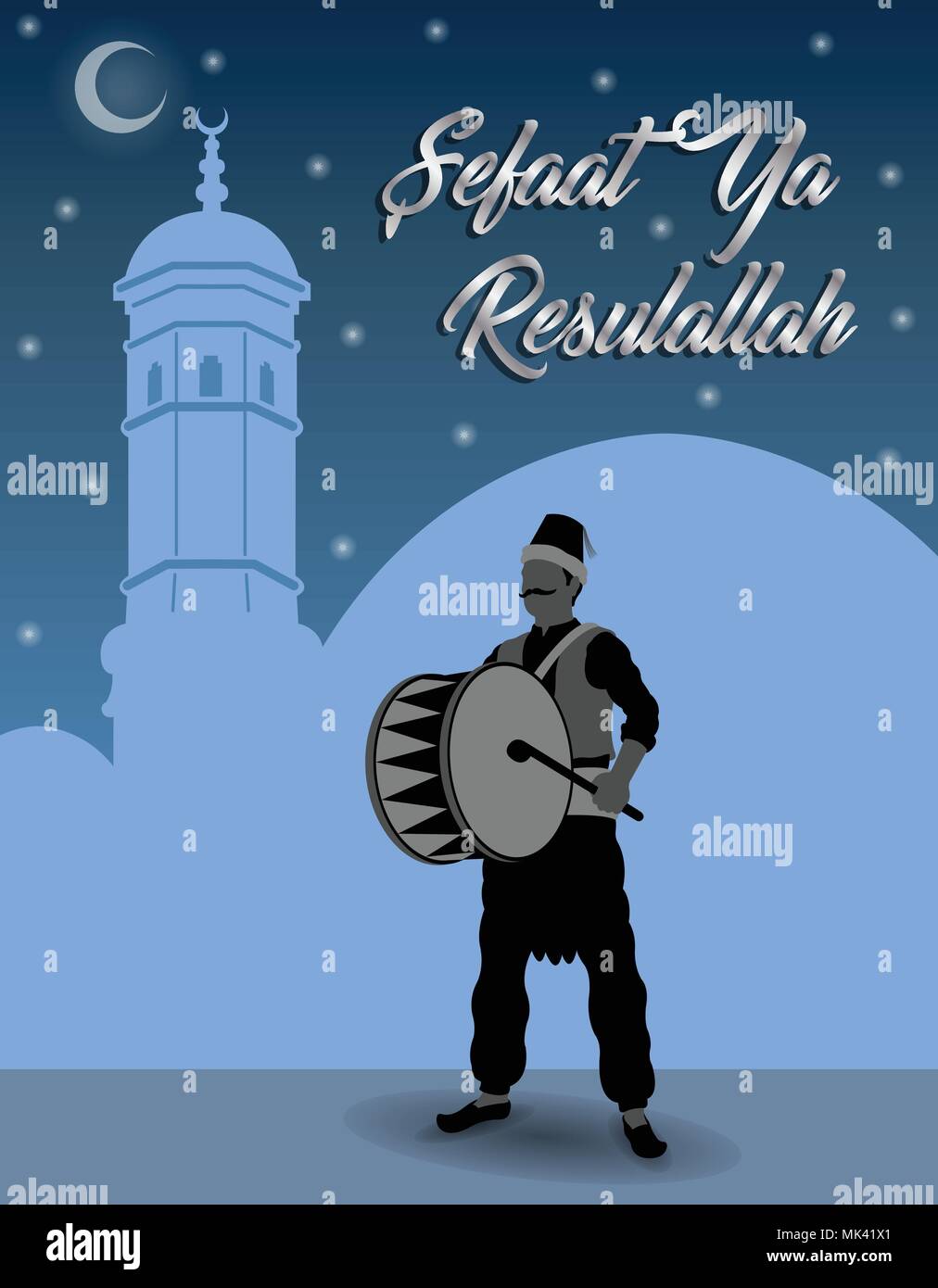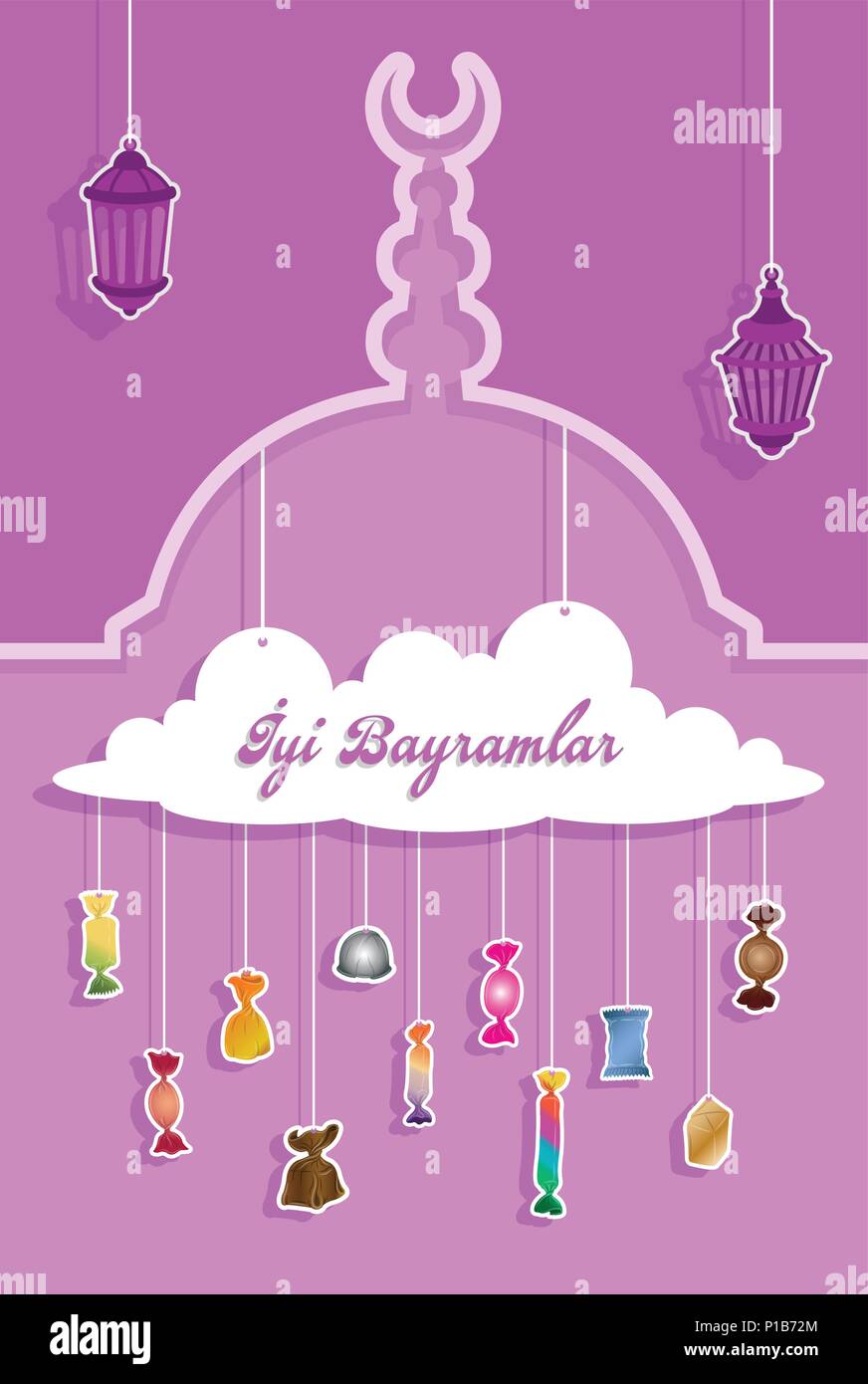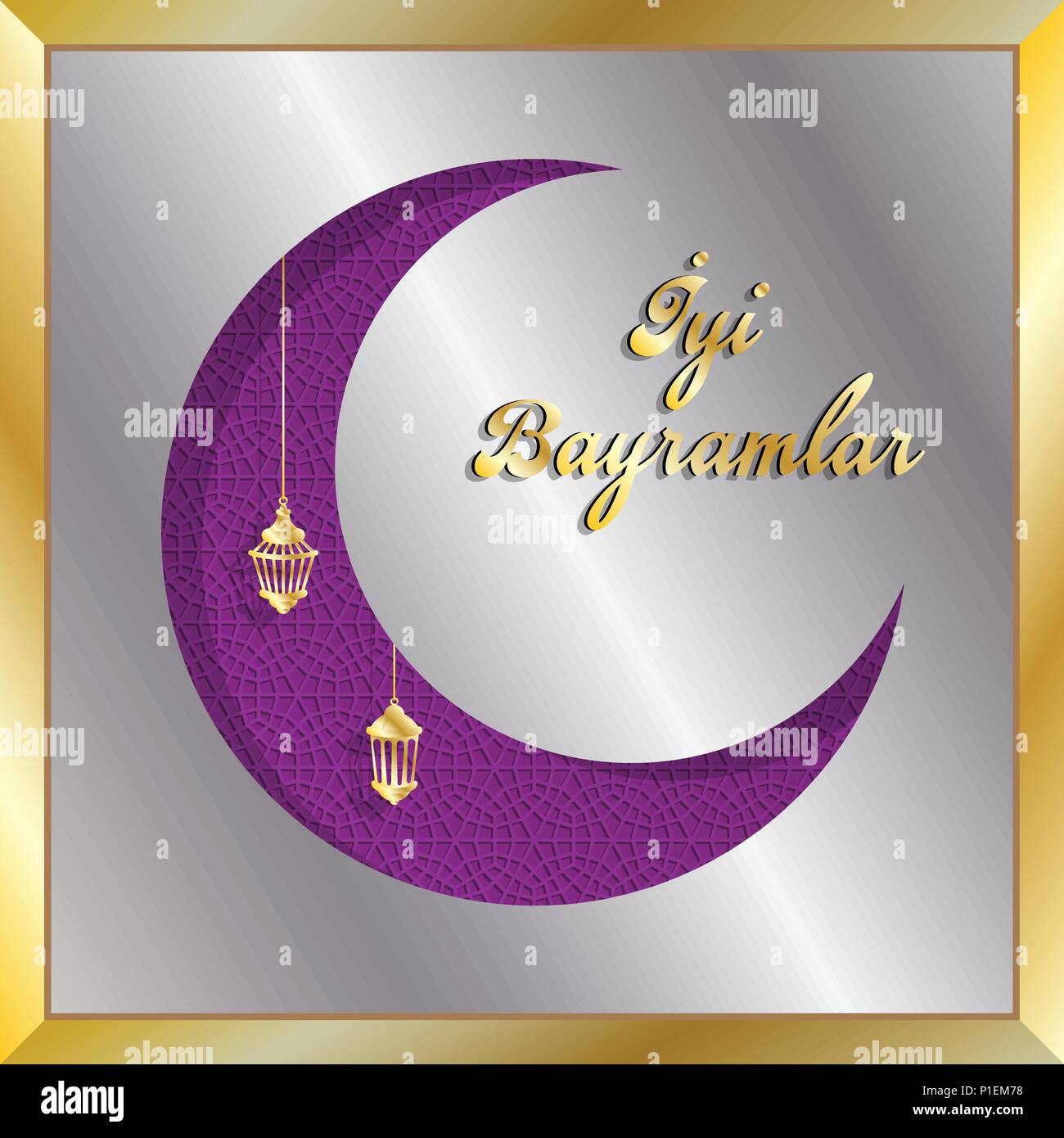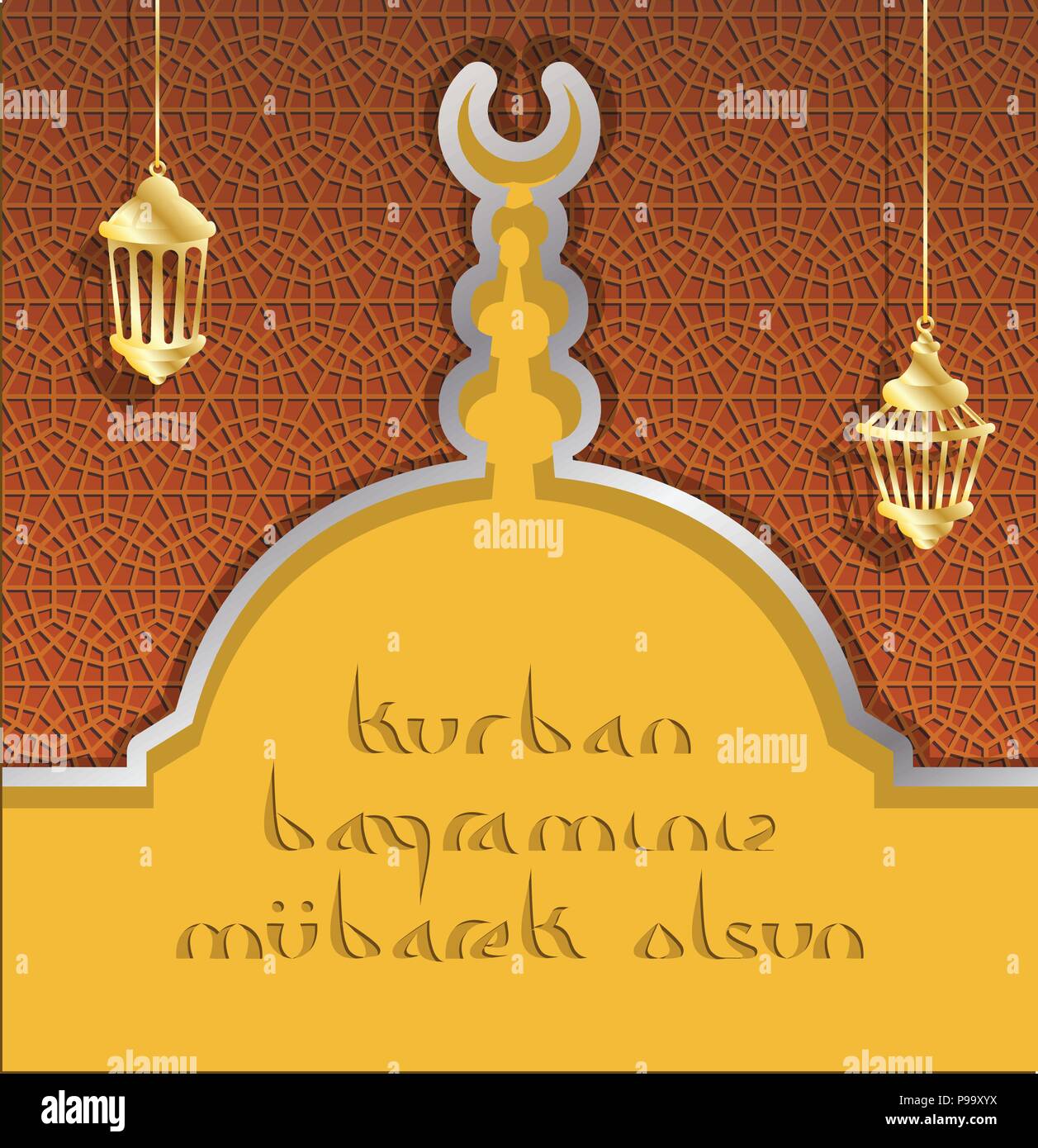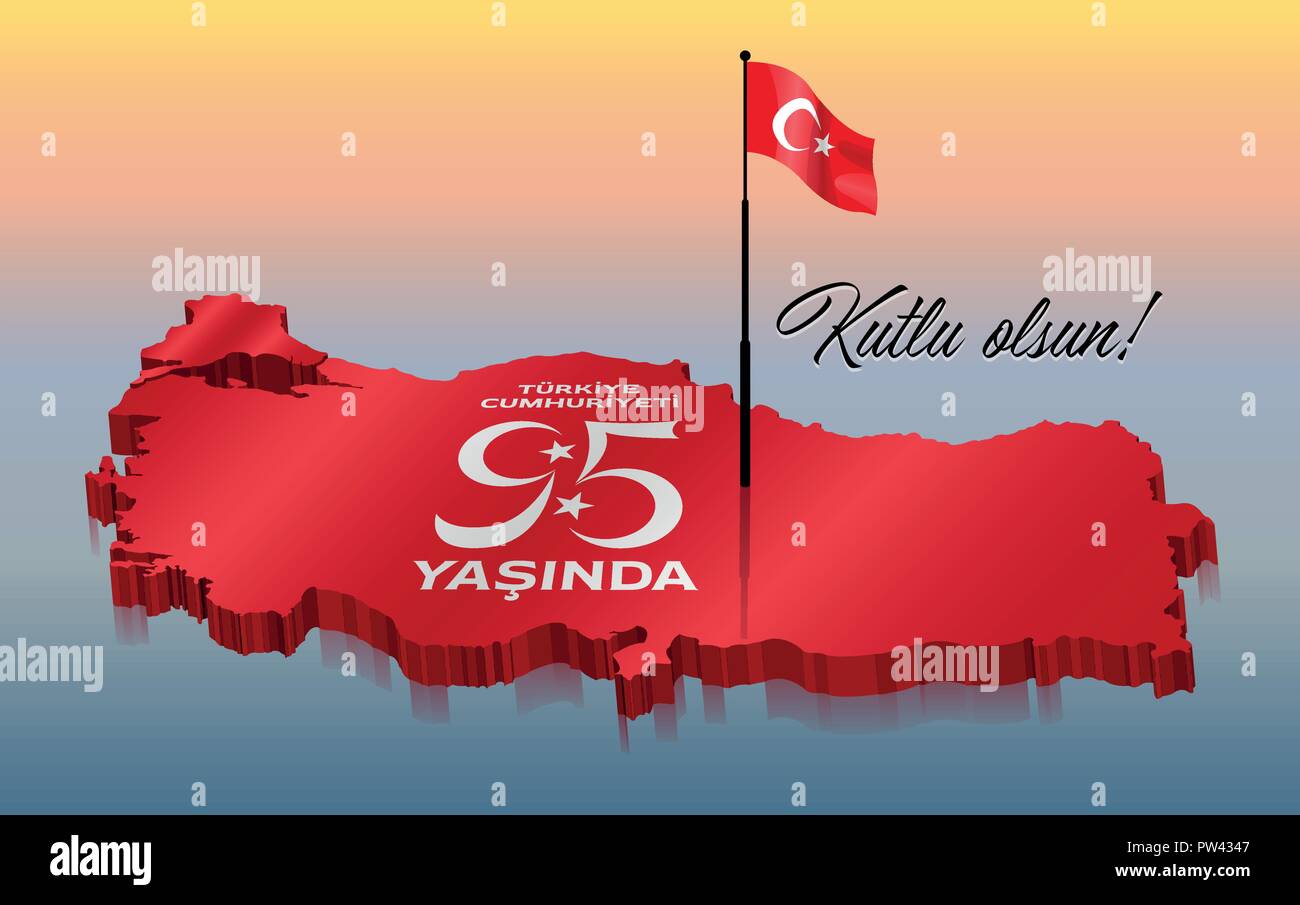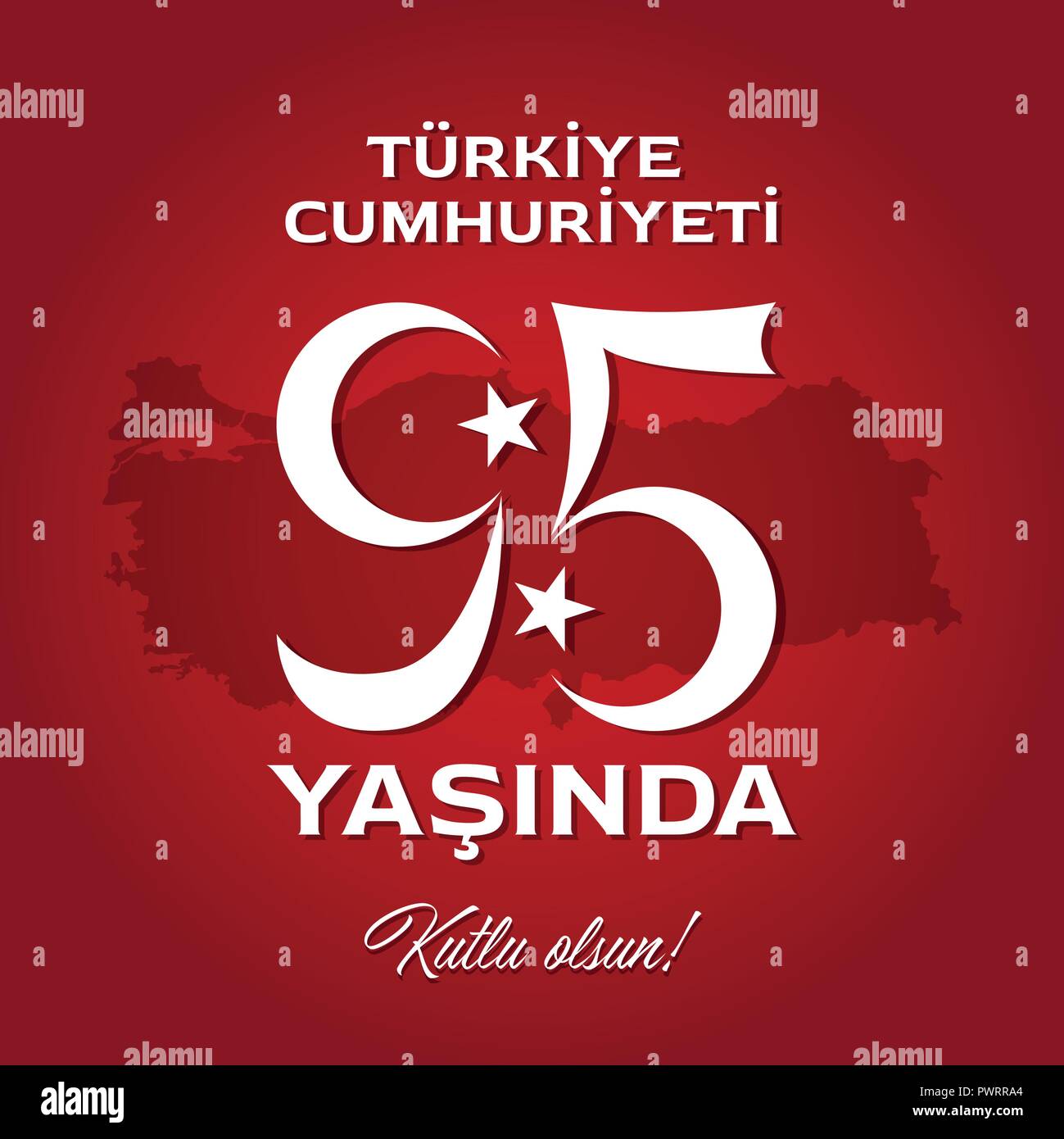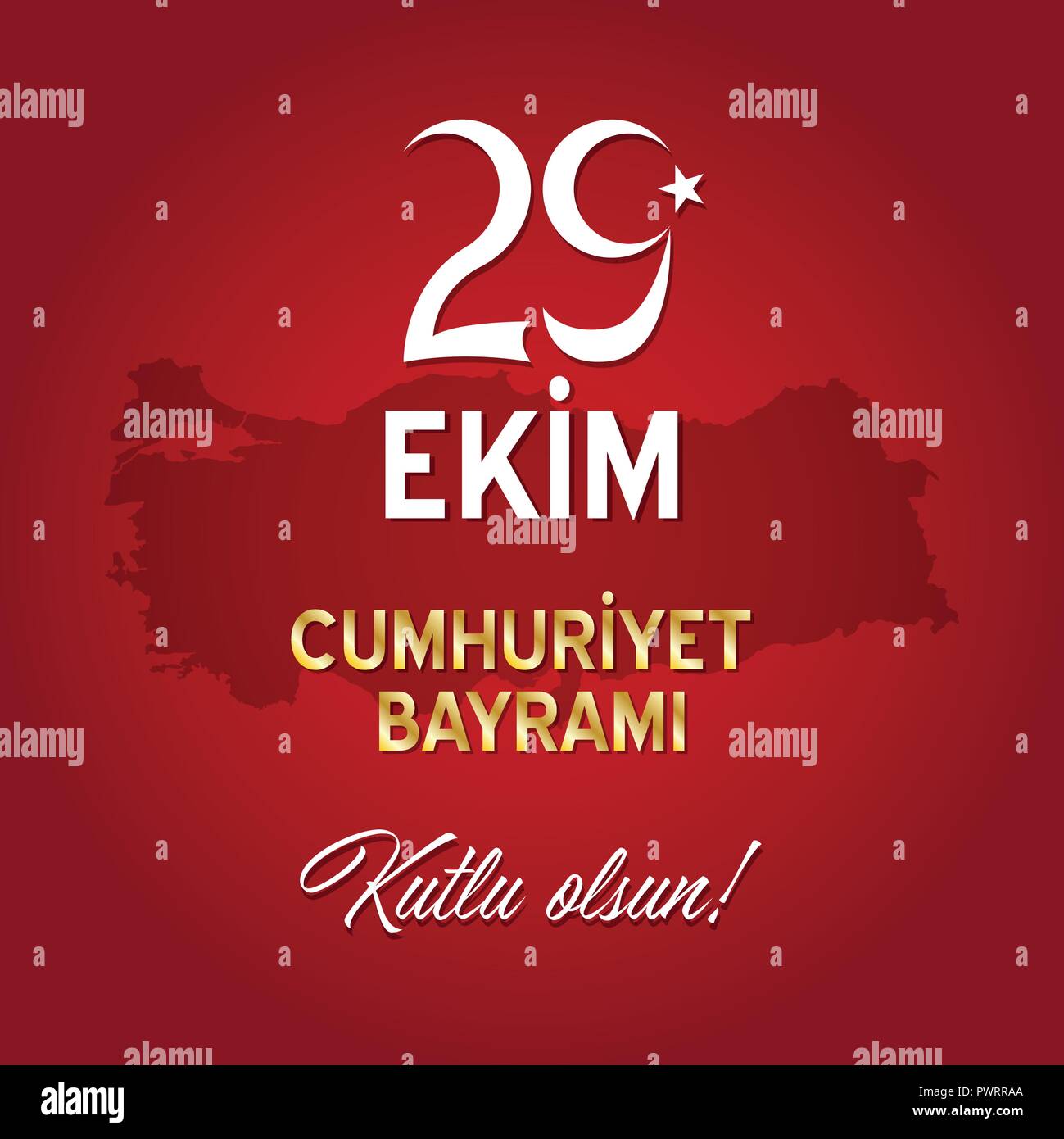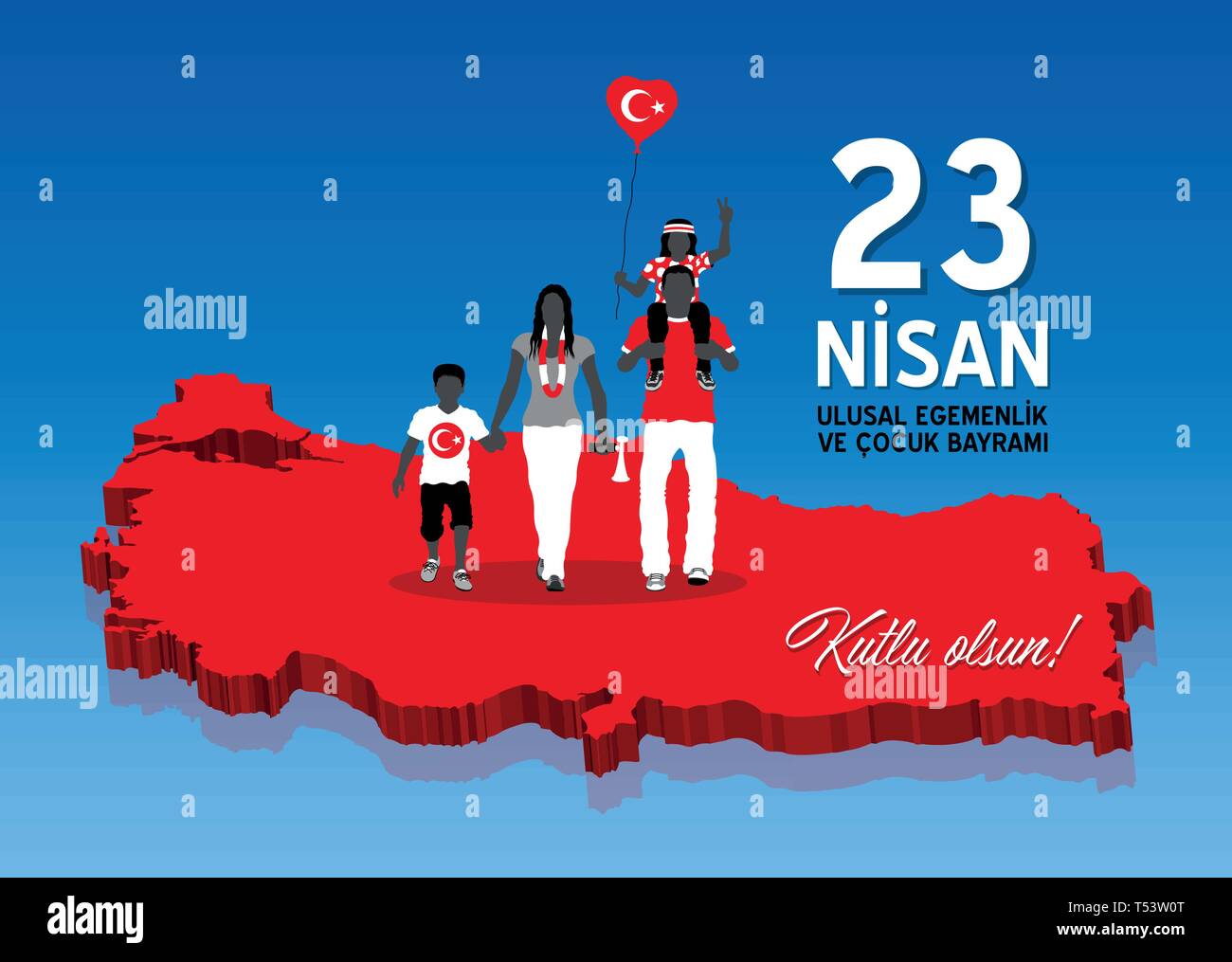
Turkische Schriftart
Turkish Airlines is the national flag carrier airline of Turkey, founded in 1933 The font used in the logo of Turkish Airlines is probably Proxima Nova ExtraBold designed by Mark Simonson in 05.
Turkische schriftart. Türkische Staatsbeamte als österreichische Religionsführer In Österreich wurde diese Praxis mit dem Islamgesetz 15 als Auslandsfinanzierung verboten ATIB gab nach der angekündigten Ausweisung von rund 40 Imamen Anfang Juni zu, dass einige Imame des Vereins auch drei Jahre nach der Reform ihr Gehalt vom türkischen Staat bezogen. In dem sie Lehnwörter durch türkische Entsprechungen ersetzt, sorgt sie für eine Modernisierung der türkischen Sprache Diese Wortneuschöpfungen werden dann als „Öztürkçe“ (Echttürkisch) bezeichnet. Search the world's information, including webpages, images, videos and more Google has many special features to help you find exactly what you're looking for.
FF Kievit Font FF Kievit is a contemporary humanist sansserif typeface designed by Michael Abbink and published through FontFont in 01 FF Kievit was first conceived by Mike Abbink in 1995 as part of a project he was working on when still a Bachelor of Fine Arts student in Pasadena, CA. Tillium Web Schriftart hat türkische Zeichenunterstützung Es gibt 16 verschiedene Schriftarten Es ist eine einfache Schriftart, die alle Grafikdesigner bevorzugen können. Download Cavolini font for PC/Mac for free, take a testdrive and see the entire character set Moreover, you can embed it to your website with @fontface support.
Download the Open Sans font by Steve Matteson The Open Sans font has been downloaded 405,417 times. Türkische Lateinalphabete sind eine Untergruppe der lateinischen Schrift, in der heute Turk und andere vorderasiatische Sprachen wie das Kurdische, Tscherkessische und Lasische geschrieben werden Sie haben geschichtlich ältere Alphabete ersetzt, deren Vorläufer in den betreffenden Sprachen auch als Einheitliches Alphabet bezeichnet wurden Die ursprüngliche Bezeichnung dieser Schriftsysteme – Einheitliches türkisches Alphabet – wurde aufgegeben, als sich auch nichttürkische. Browse the Font Squirrel fonts tagged as Turkish About Font Squirrel is your best resource for FREE, handpicked, highquality, commercialuse fonts.
Ausgewählte Schriftart, Schriftgröße und Effekte gelten für die gesamte Notiz If you have selected a font , font size, or special effect, it is in force for the entire note Ändert die Schriftart für das Texttool. Wenn Sie Zeichen aus einem anderen Sprachraum eingeben möchten, müssen Sie die Tastatursprache ändern Dann können Sie zB auch arabische Zeichen verwenden. HELVETICA & HELVETICA NEUE FONTS Where did Helvetica come from?.
Gewusst wie Tamil Schriftarten in MS Word verwenden Microsoft Word bietet vollständige Unterstützung für die Sprache Tamil Für schnelle Betrachtung Unterstützung ist die universelle SchriftartOption als Teil des Microsoft Office International Support eingebaut Um Zugriff auf eine breitere Vielzahl. This typeface is also available within Office applications For more information visit this page Style & weight examples Change list Windows 10 version 1507 released on July 29, 15. Nummernschild Generator eigene Kennzeichen und Wunschkennzeichen erstellen Alles dabei normale PKW und Motorrad (FE), die alten DIN, Bundeswehr und die neuen kleinen Motorrad 11 Schilder!.
The line \usepackage{tgbonum} establishes the font family T e X Gyre Bonum, whose font package name is tgbonum, as the default font for this document Open an example in Overleaf Changing default font typeface The font can also be changed for a specific element in the document. Eine passende Schriftart zu finden kann im Normalfall schon ziemlich schwierig sein, aber arabische, orientalische und türkische Schriftarten dürfen auf keinen Fall verwechselt werden!. Making the web more beautiful, fast, and open through great typography.